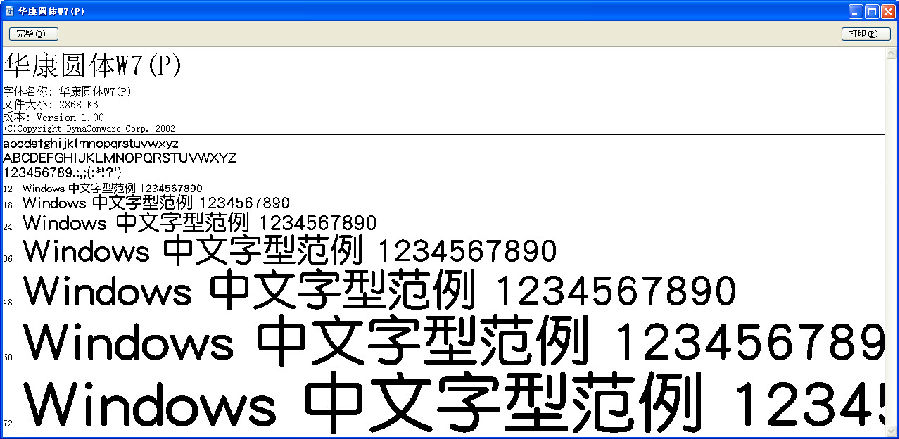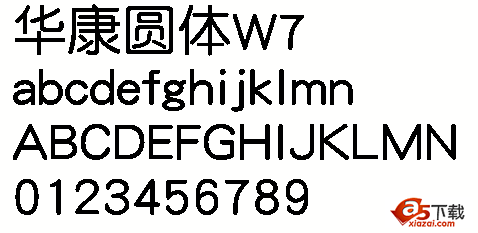
華康圓體w7字體是一種外形非常美觀的華康字體。本字體即可以用在平面設(shè)計(jì)上,也可以用于日常辦公使用。字體輸出端文字信息規(guī)范有朝氣!喜歡的用戶歡迎來(lái)綠色資源網(wǎng)下載使用。
華康圓體W7是一套完全別于明黑楷的內(nèi)文字設(shè)計(jì),柔合了黑體的簡(jiǎn)潔加添了圓混柔和之感觀,字型筆劃簡(jiǎn)單,圓頭圓尾,骨格外張內(nèi)弛,反明黑內(nèi)文字之嚴(yán)肅氣氛。細(xì)圓于排內(nèi)文時(shí)感覺(jué)特別均衡,字行感額外明顯。適合用在廣告?zhèn)鲉?,說(shuō)明小冊(cè)本,手提書(shū)刊,報(bào)表,名片等(非公文性的)。